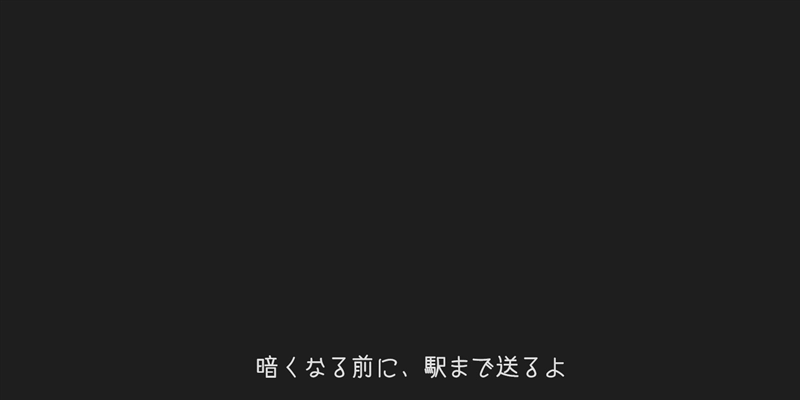
字幕デザインのフォント
しねきゃぷしょん(cinecaption) フォントの作例
しねきゃぷしょん(cinecaption) フォントの作例です。
概要
映画の字幕の文字のデザインのフォントです。
字幕系フォントの中でも手描き感のあるデザインの書体です。
しねきゃぷしょん(cinecaption) フォントの作例:画像1